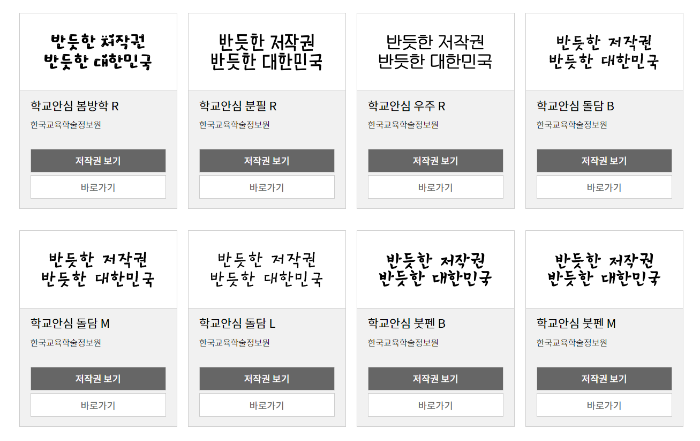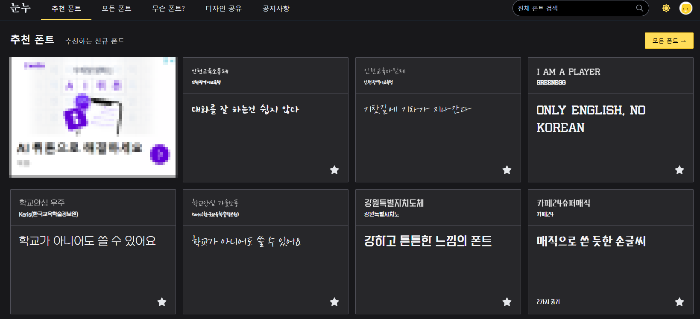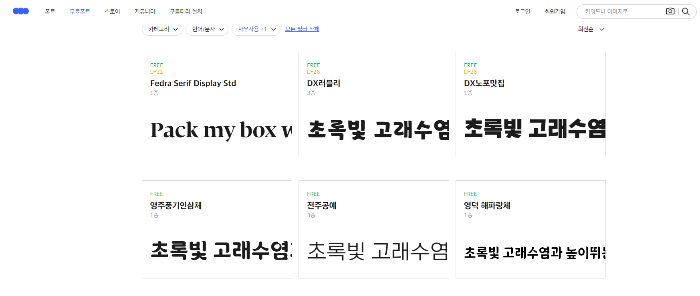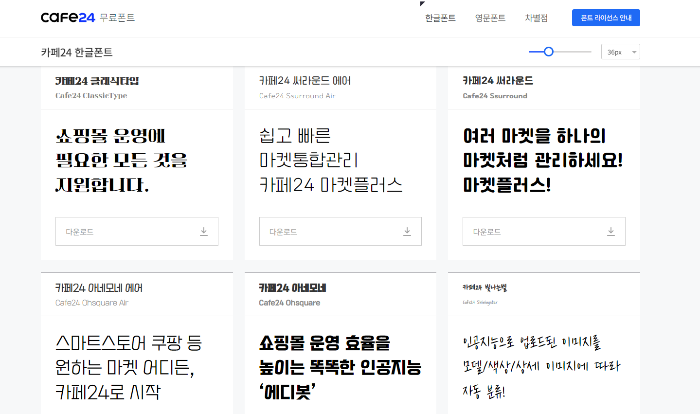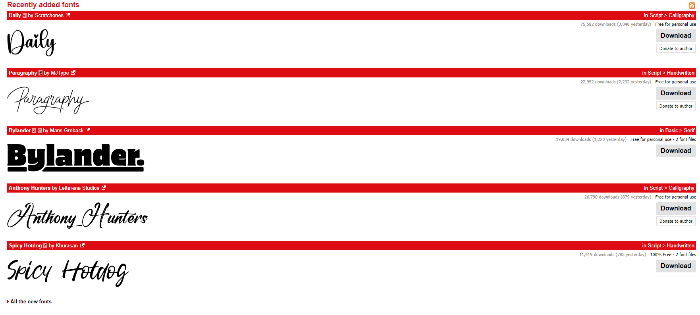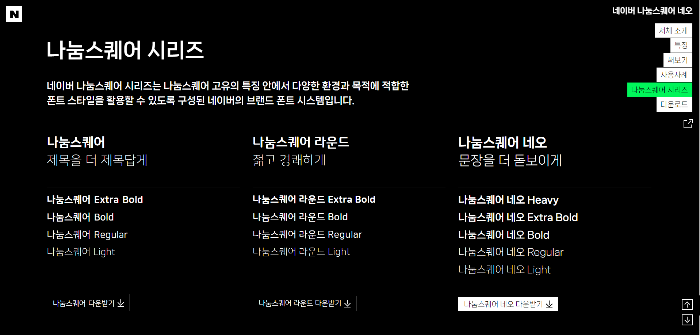
디자이너 추천 상업용 한글 영어 무료 폰트 다운로드 사이트 7
디자인 작업 시 폰트는 글의 가독성을 높일 뿐 아니라 디자인적인 면에서도 크게 작용하게 됩니다. 예전 블로그에 작업물을 올렸다가 폰트 때문에 법무법인 연락을 어찌나 많이 받았던지 그 괴로움은 이루 말할 수가 없었어요. 여러분들도 저 같은 실수하지 말고 상업용 한글 무료폰트 사이트에서 걱정 없이 다운로드하여 사용하시길 바랍니다. 상업용으로 사용 가능한 한글 영어 무료 다운로드 사이트에 대해 자세히 알아보겠습니다.
상업용 무료폰트 다운로드 사이트
상업용 무료 폰트란?
눈누
눈누는 상업용 무료 폰트 중 가장 다양한 데다 예쁜 폰트들이 많고 폰트 미리 보기 기능도 있어 직접 폰트를 사용해 보고 다운로드할 수 있습니다. 원하는 폰트를 클릭하면 라이선스를 확인할 수 있습니다.
네이버 나눔 폰트
폰트가 깔끔하고 개인적으로 가독성이 필요한 글 쓸 때 많이 사용합니다. 원하는 폰트를 직접 작성해 보고 다운로드할 수 있습니다. 폰트 유료 판매 외 모든 상업적 사용이 가능합니다.
구글폰트
구글폰트의 가장 큰 장점은 다양한 나라의 언어를 검색해 사용해 보고 다운로드할 수 있다는 점입니다. 반면 한글 폰트는 다소 부족하고 개인적으로 예쁜 폰트보다는 가독성이 좋은 폰트인 거 같습니다.
카페 24
공유마당
주로 기관이나 지역폰트로 이루어져 있고 일부 영문폰트도 있습니다. 개인적으로 캘리그래피 유사한 폰트가 마음에 듭니다. 폰트는 재판매를 제외하고 모든 곳에 사용가능합니다.
산돌구름
아기자기하고 다양한 한글폰트가 많고 구름다리 프로그램 설치 후 다운로드 가능합니다. 단, 일부 범위제한 폰트가 있으니 꼭 확인하고 사용하시 길 바랍니다.
dafont
dafont 최대 장점은 엄청난 양과 다양하고 멋진 영문폰트가 많다는 점입니다. 영문폰트가 필요할 때는 망설이지 말고 dafont를 선택하세요.